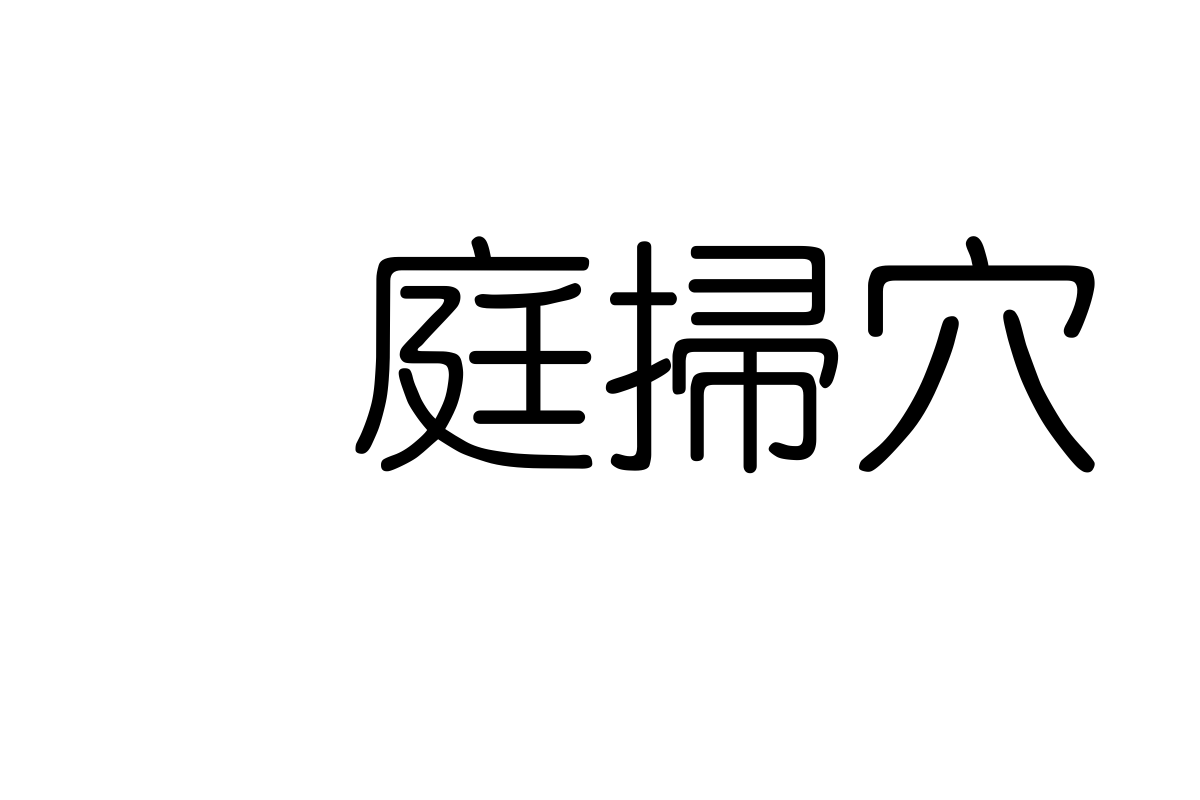
汉仪细中圆繁字体是一套由汉仪公司开发的中文字体,专为中文排版设计而制作。这套字体以其独特的风格和特点,在众多中文字体中脱颖而出。
首先,汉仪细中圆繁字体的字形结构非常独特,笔画粗细适中,线条流畅,给人一种优雅、精致的感觉。这种独特的字形结构使得它在视觉上具有很强的辨识度,能够很好地适应各种应用场景,如标题、正文、广告等。
其次,汉仪细中圆繁字体的字体风格也非常独特,既有传统的韵味,又不失现代感。它的字形圆润饱满,线条柔和,给人一种温馨、亲切的感觉。这种风格使得它在传达情感和氛围方面具有很高的效果,能够很好地吸引读者的注意力。
最后,汉仪细中圆繁字体的适用范围非常广泛,无论是用于书籍、杂志、报纸、广告还是网页设计,都能够展现出其独特的魅力。它的可读性和美观性都非常高,能够满足不同用户的需求。
总的来说,汉仪细中圆繁字体是一款非常优秀的中文字体,无论是在视觉效果还是实用性方面都表现出色。它为设计师提供了更多的选择,也为他们的作品增添了更多的可能性。